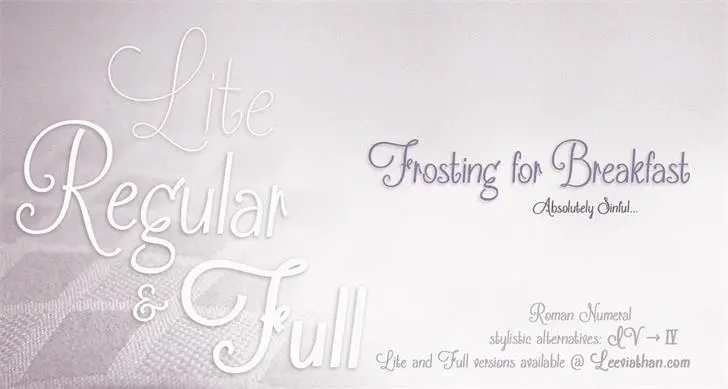
Frosting for Breakfast font – Fonte Grátis
Frosting for Breakfast font
Esta font ‘Frosting for Breakfast’ é ideal para quem procura uma escrita fluida e elegante para aplicar em designs pessoais ou comerciais. Cada caractere dessa fonte, cuidadosamente criado pelo designer Hamilton, transmite um toque suave e descontraído que vai deixar seu projeto destilando personalidade. Através de sua estrutura arredondada e harmoniosa, a ‘Frosting for Breakfast’ é uma opção ideal para criar letras chamativas em cartazes, logotipos ou até mesmo capas de livros. Suas linhas leves e curvas suaves não só destacam o texto ao qual está aplicado, mas também criam um ar leve e acolhedor que se encaixa perfeitamente para ambientes onde você deseja transmitir uma mensagem alegre e descontraída. Ela é especialmente adequada para designers gráficos atentos à estética. Não só oferece um toque especial ao seu design, mas também é projetada com facilidade de uso em mente, permitindo que o designer possa explorar diferentes ambientes sem grandes sacrifícios na qualidade da escrita. Com a conveniência de ser gratuita tanto para uso pessoal quanto comercial, e a opção de se envolver um pouco mais doando à Hamilton, quem encontrar esse design charmoso está prestes a ganhar uma fonte que vai tornar seu próximo projeto ainda melhor.